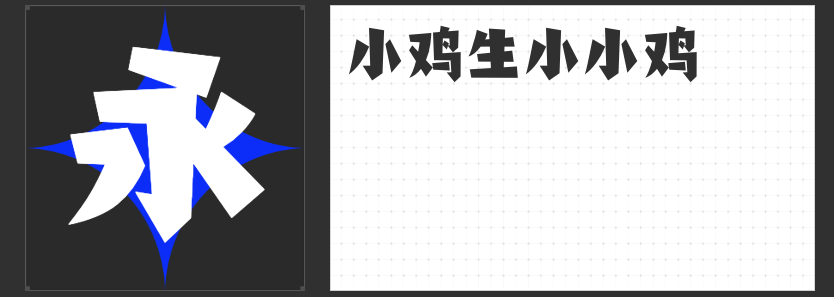
设计也要有创意,四款匠心字体赋能书籍封面美学
书籍封面是文字与视觉艺术的交融场域,字体作为核心视觉元素,既要承载内容气质,又要构建独特的审美意境。以下四款字体以创新设计语言打破传统书体框架,为不同题材的书籍封面设计提供多元美学选择。
一、励字志向黑简 超粗
这款字体以黑体为骨架,通过圆角处理打破方正结构的冷硬感。笔画转折处的微弧设计如同书页边缘的柔和卷曲,在超粗字重中注入人文温度。其字面充实、结构稳定的特点,既能驾驭历史社科类书籍的厚重感,又因屏显适配性成为电子书封面的理想选择。圆体与黑体的融合创新,让文字在保持现代简约风格的同时,暗含东方哲学中“刚柔并济”的智慧。
二、励字综艺简繁
通过极致的笔画加粗与空间填充,这款字体构建出充满张力的视觉场域。方正的骨架中暗藏圆润转角,如同书法中“藏锋”的笔意,在严谨的几何结构中注入流动韵律。繁简体同步开发的设计思维,使其既能呈现古典文学的雅致,亦可诠释现代思潮的锋芒。横平竖直的笔画中,细微的粗细变化暗合阅读节奏,让封面文字成为引导读者进入文本世界的视觉路标。
三、励字山中精灵简
以“圆润萌动”为设计核心,这款字体通过饱满笔画与留白空间的精妙配比,营造出山林雾气的空灵质感。转角处的弧线处理如同晨露滑落叶尖,布白均匀的节奏感暗合自然呼吸韵律。其可拉伸特性赋予设计师更大的创作自由,无论是竖排古诗的古典意境,还是儿童绘本的活泼氛围,都能通过字体形态的微调实现完美适配。
四、励字俊林简
取法竹叶形态的笔画设计,让这款字体自带清雅气质。圆融转角与留白空间的对话,构建出“疏影横斜”的东方美学意境。相较于传统书法字体,其标准化的简体编码与统一风格设计,使文字在保持艺术性的同时更具现代传播力。无论是哲学著作的深邃思考,还是艺术画册的视觉叙事,都能通过字体的清雅韵味强化内容调性。
这四款字体以不同维度解构文字美学,从力量感到萌动感,从秩序感到自然感,为书籍封面设计提供丰富的表达工具。设计师可依据文本内核选择适配字体,让封面文字成为连接内容与读者的第一座美学桥梁。